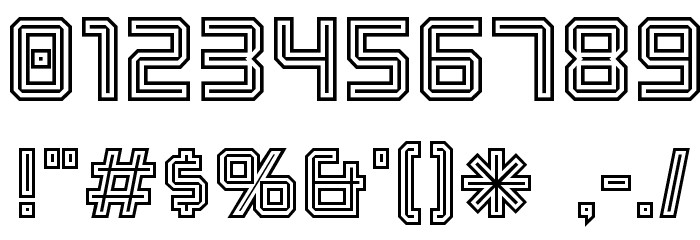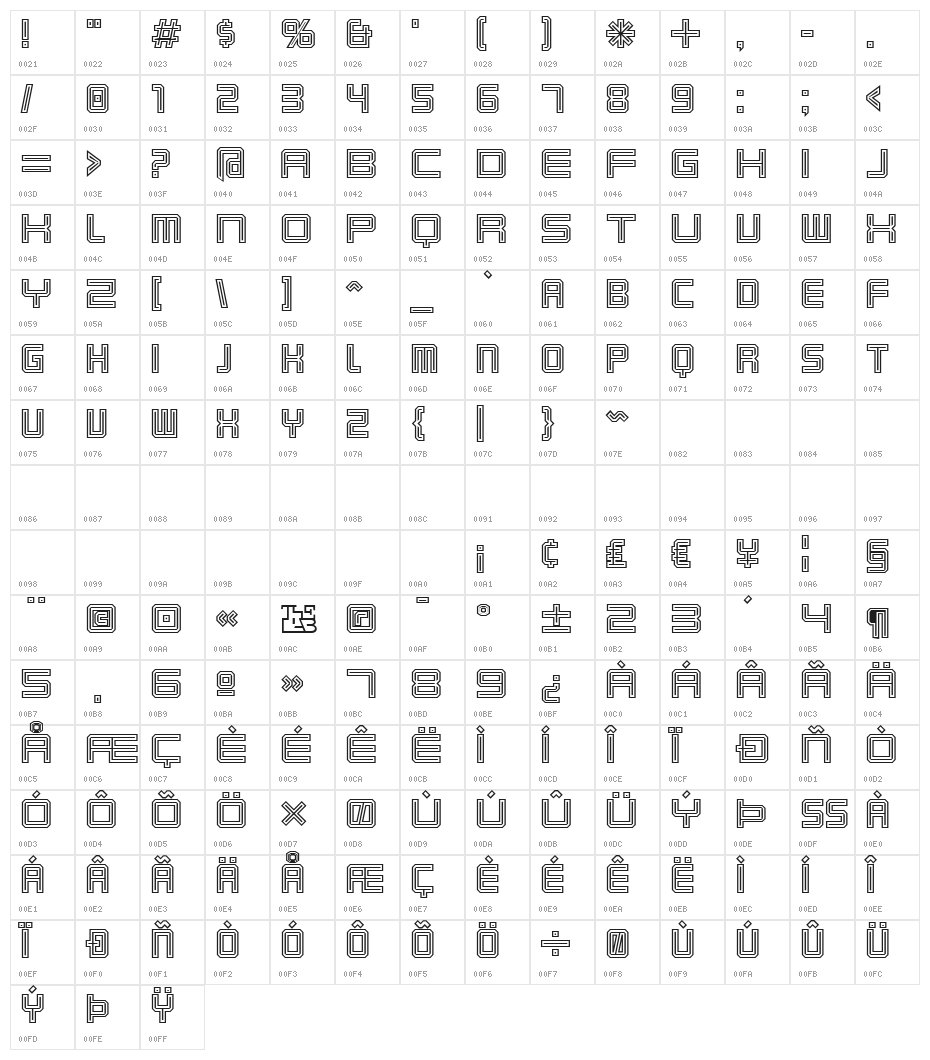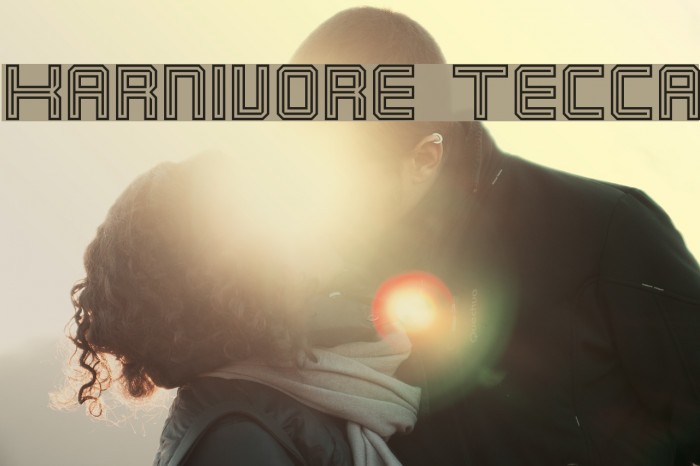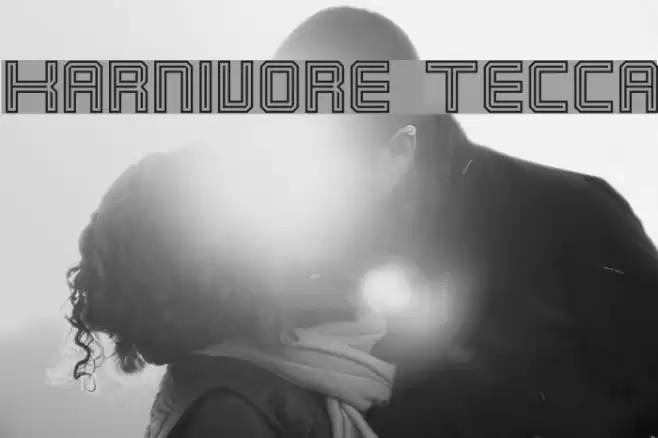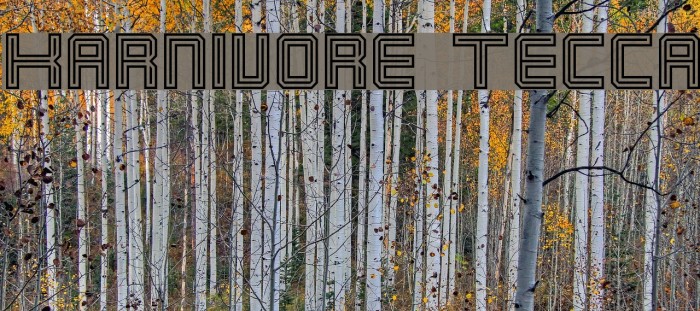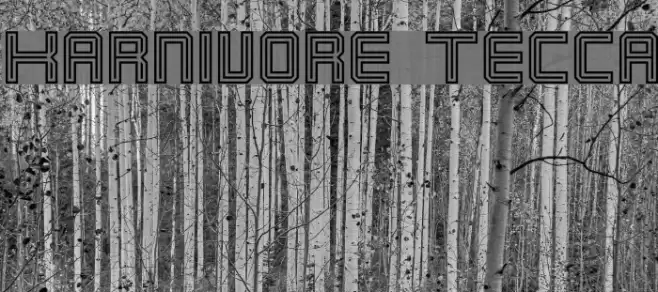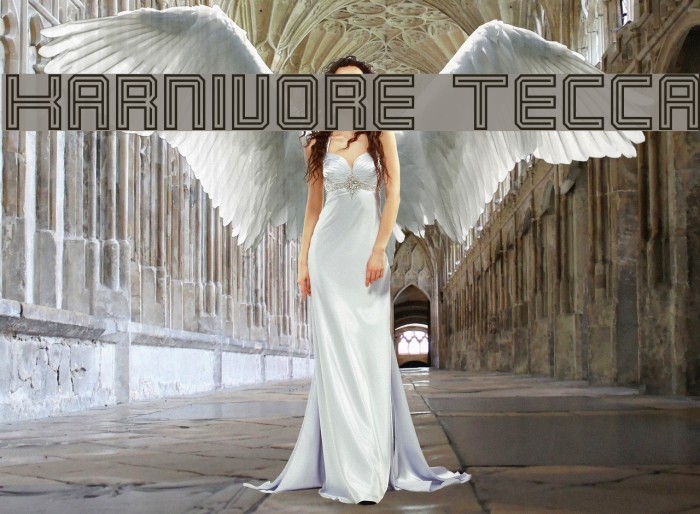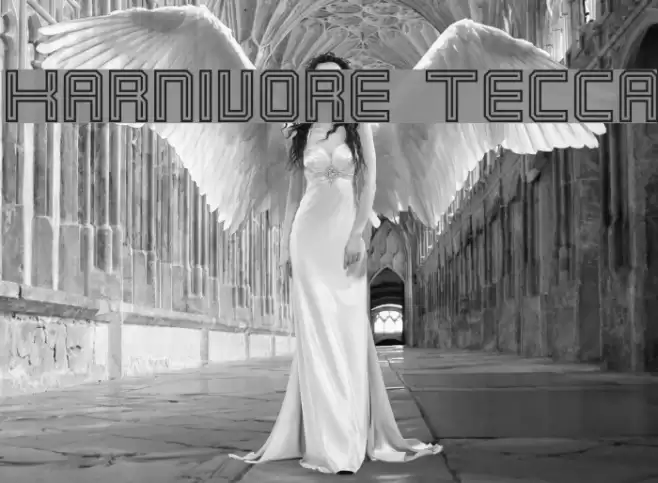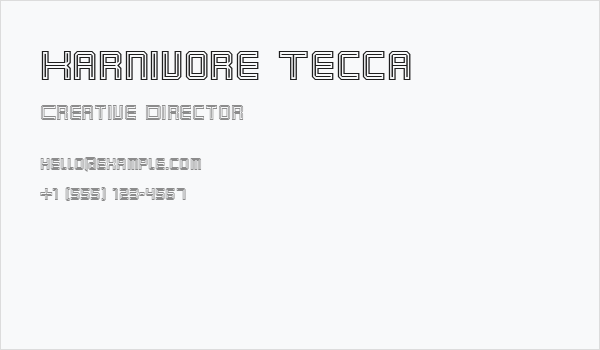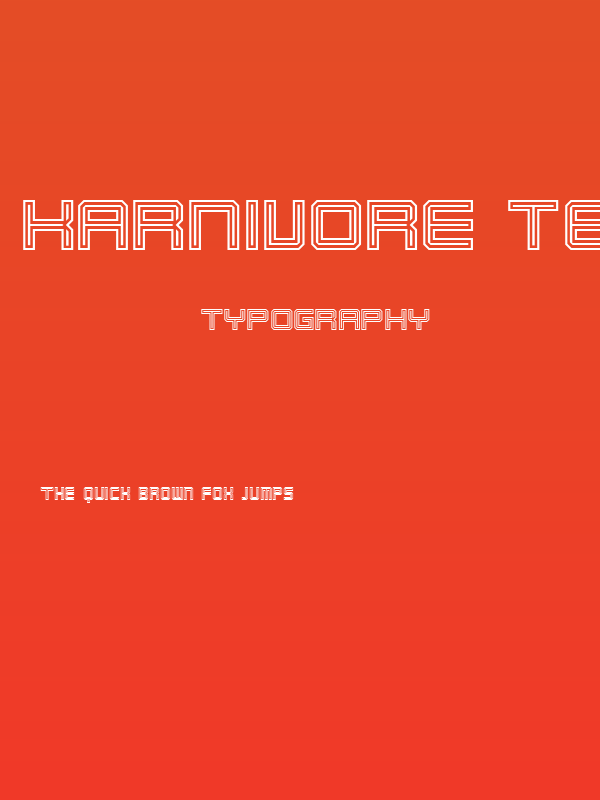
Karnivore Tecca Font
✎ Outline
| Vorgeschlagene Projekte | Ideal for branding, posters, album covers, and digital artwork that require a modern and edgy aesthetic. |